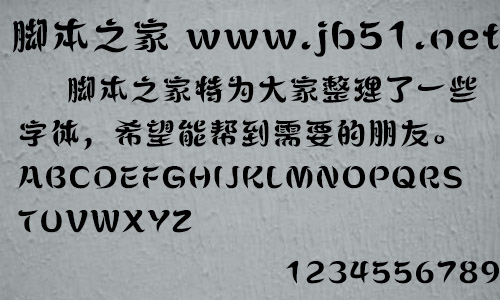
方正飛躍體簡Heavy是由方正字庫最新開發(fā)的一款中文藝術(shù)字體,又可以稱為方正飛躍體簡特大字體,字體帶有非常活躍的氣氛,還想每一筆都忍不住想要跳起來,字體整體具有很強的辨識度,適合應(yīng)用于藝術(shù)設(shè)計、平面宣傳設(shè)計、網(wǎng)頁設(shè)計,書法字貼等領(lǐng)域,需要的朋友可以前來本站下載。